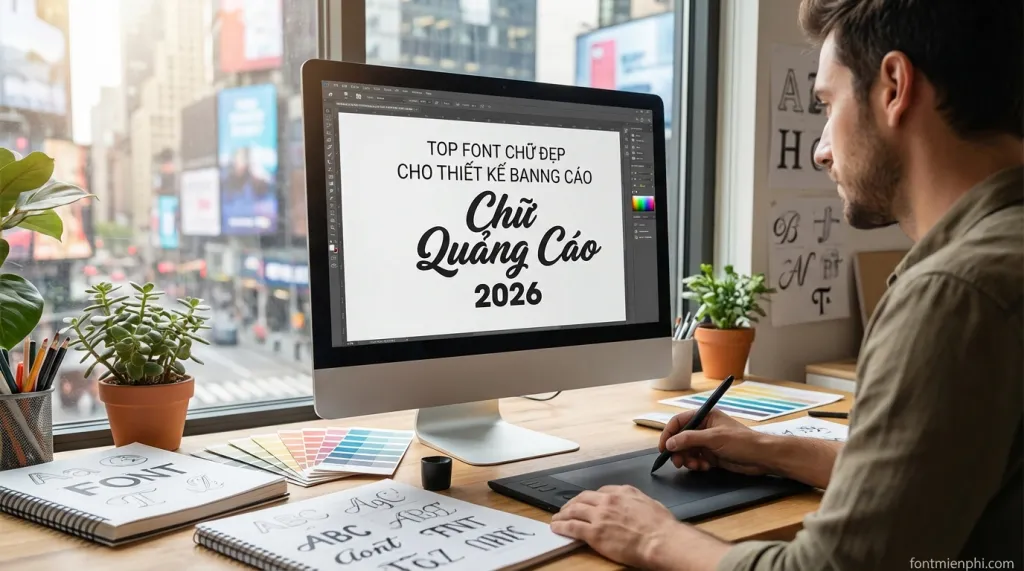
Trong bối cảnh quảng cáo kỹ thuật số ngày càng cạnh tranh, việc lựa chọn font chữ phù hợp cho banner không chỉ là một quyết định thẩm mỹ mà còn là yếu tố chiến lược quyết định hiệu quả truyền thông. Một font chữ đẹp, dễ đọc và phù hợp có thể ngay lập tức thu hút sự chú ý, truyền tải thông điệp rõ ràng và củng cố nhận diện thương hiệu. Bài viết này sẽ đi sâu phân tích tầm quan trọng của font chữ, các nguyên tắc lựa chọn, dự đoán xu hướng cho năm 2026 và giới thiệu những font chữ hàng đầu, giúp bạn tạo ra những banner quảng cáo tối ưu và ấn tượng nhất.
Top Font Chữ Đẹp Cho Thiết Kế Banner Quảng Cáo 2026
I. Tầm Quan Trọng Của Font Chữ Trong Thiết Kế Banner Quảng Cáo
Font chữ không chỉ là phương tiện truyền tải văn bản; chúng là một phần không thể thiếu của ngôn ngữ hình ảnh, mang theo cảm xúc, phong cách và cá tính riêng. Trong lĩnh vực thiết kế banner quảng cáo, nơi mà mỗi mili giây đều quý giá để thu hút sự chú ý của người xem, việc lựa chọn font chữ đóng vai trò then chốt. Một font chữ được chọn lọc kỹ lưỡng có thể biến một thông điệp đơn thuần thành một tuyên bố mạnh mẽ, dễ dàng đi vào tâm trí khách hàng mục tiêu.
Vai trò của font chữ trong banner quảng cáo có thể được nhìn nhận qua nhiều khía cạnh. Đầu tiên, chúng giúp tạo ra ấn tượng đầu tiên. Trong một không gian kỹ thuật số đầy rẫy thông tin, banner quảng cáo chỉ có vài giây để gây ấn tượng. Font chữ độc đáo, phù hợp có thể làm nổi bật banner của bạn giữa hàng trăm quảng cáo khác, kích thích sự tò mò và khuyến khích người xem dừng lại để đọc kỹ hơn. Thứ hai, font chữ truyền tải cảm xúc và giá trị thương hiệu. Một font serif cổ điển có thể gợi lên sự sang trọng và đáng tin cậy, trong khi một font sans-serif hiện đại lại thể hiện sự năng động và thân thiện. Việc lựa chọn font chữ đồng điệu với bản sắc thương hiệu giúp củng cố thông điệp và xây dựng nhận diện thương hiệu nhất quán. Thứ ba, tính dễ đọc của font chữ quyết định khả năng truyền tải thông điệp. Banner quảng cáo thường chứa thông tin ngắn gọn, súc tích. Nếu font chữ quá cầu kỳ, khó đọc hoặc không phù hợp với kích thước hiển thị, thông điệp sẽ bị mất đi, dẫn đến lãng phí nỗ lực và chi phí quảng cáo. Cuối cùng, font chữ góp phần tạo nên sự khác biệt. Trong một thị trường cạnh tranh, việc sử dụng các font chữ độc đáo, chưa phổ biến hoặc được tùy chỉnh có thể giúp thương hiệu của bạn nổi bật, tạo dấu ấn riêng trong tâm trí khách hàng.
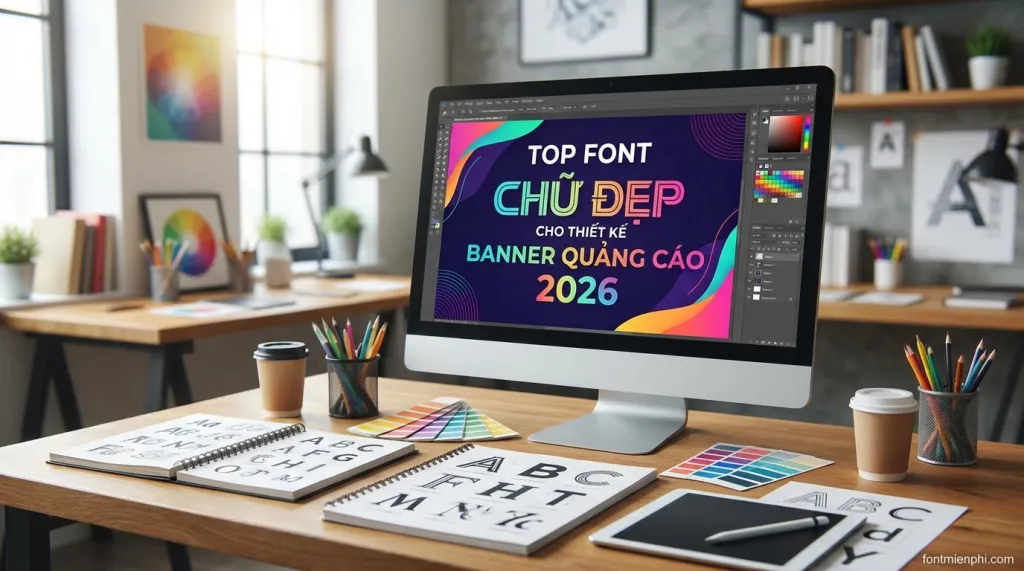
II. Các Nguyên Tắc Vàng Khi Lựa Chọn Font Chữ Cho Banner Quảng Cáo
Để tối ưu hóa hiệu quả của banner quảng cáo, việc lựa chọn font chữ cần tuân thủ một số nguyên tắc cơ bản nhưng vô cùng quan trọng. Những nguyên tắc này không chỉ đảm bảo tính thẩm mỹ mà còn nâng cao khả năng truyền tải thông điệp và tương tác với người xem.
1. Tính Dễ Đọc (Legibility)
Đây là nguyên tắc hàng đầu và không thể bỏ qua. Font chữ dù đẹp đến mấy cũng trở nên vô nghĩa nếu người xem không thể đọc được nội dung. Đối với banner quảng cáo, nơi không gian và thời gian đều hạn chế, tính dễ đọc càng trở nên cấp thiết.
– Chọn font có khoảng cách chữ (kerning) và khoảng cách dòng (leading) hợp lý.
– Tránh các font quá mảnh, quá cầu kỳ hoặc có độ tương phản thấp với màu nền.
– Đảm bảo font chữ hiển thị rõ ràng trên nhiều kích thước màn hình và thiết bị khác nhau, từ điện thoại di động đến màn hình máy tính lớn.
– Ưu tiên các font có các ký tự rõ ràng, không dễ nhầm lẫn (ví dụ: “I” và “l”, “0” và “O”).
2. Phù Hợp Với Thương Hiệu Và Thông Điệp
Font chữ phải là một phần mở rộng của bản sắc thương hiệu và nội dung quảng cáo.
– Nếu thương hiệu của bạn hướng đến sự sang trọng, cao cấp, các font serif cổ điển hoặc hiện đại có thể là lựa chọn lý tưởng.
– Đối với các thương hiệu công nghệ, startup hoặc muốn thể hiện sự hiện đại, năng động, font sans-serif thường được ưu tiên.
– Thông điệp quảng cáo cũng ảnh hưởng đến việc chọn font. Một chương trình khuyến mãi giảm giá có thể dùng font mạnh mẽ, thu hút, trong khi thông điệp về sự bền vững, thân thiện môi trường có thể dùng font mềm mại, hữu cơ hơn.
– Đảm bảo sự đồng bộ với các kênh truyền thông khác của thương hiệu để tạo sự nhận diện nhất quán.
3. Khả Năng Mở Rộng (Scalability)
Banner quảng cáo xuất hiện ở nhiều vị trí và kích thước khác nhau. Một font chữ tốt phải giữ được tính dễ đọc và thẩm mỹ khi được phóng to hay thu nhỏ.
– Font chữ cần duy trì độ sắc nét, không bị vỡ nét hay mờ khi thay đổi kích thước.
– Kiểm tra font trên các mock-up banner ở nhiều kích thước khác nhau trước khi đưa vào sử dụng chính thức.
– Các font được thiết kế tối ưu cho web (web-safe fonts) thường có khả năng mở rộng tốt hơn.
4. Cảm Xúc Và Tâm Lý Học Font Chữ
Mỗi loại font chữ mang một “tính cách” và gợi lên những cảm xúc khác nhau.
– **Serif:** Gợi cảm giác truyền thống, đáng tin cậy, sang trọng, uy tín (thường dùng cho các ngành tài chính, luật, giáo dục, thời trang cao cấp).
– **Sans-serif:** Hiện đại, tối giản, thân thiện, dễ tiếp cận, rõ ràng (phổ biến cho công nghệ, thương mại điện tử, dịch vụ).
– **Script/Handwritten:** Nghệ thuật, cá tính, độc đáo, thân mật (thường dùng cho các sản phẩm thủ công, sự kiện đặc biệt, thương hiệu cá nhân).
– **Display:** Mạnh mẽ, thu hút, độc đáo, thường dùng cho tiêu đề lớn, tạo điểm nhấn mạnh (giải trí, game, sản phẩm mới).
Hiểu rõ tâm lý học font chữ giúp bạn lựa chọn font phù hợp nhất với mục tiêu truyền thông.
5. Hỗ Trợ Đa Ngôn Ngữ Và Ký Tự Đặc Biệt
Đối với thị trường Việt Nam, việc font chữ hỗ trợ đầy đủ các ký tự tiếng Việt (dấu, chữ cái đặc biệt như “ă”, “â”, “đ”, “ê”, “ô”, “ơ”, “ư”) là yếu tố cực kỳ quan trọng.
– Một font không hỗ trợ tiếng Việt sẽ dẫn đến hiện tượng lỗi font, các ký tự bị biến dạng hoặc hiển thị không đồng nhất, gây ảnh hưởng nghiêm trọng đến tính chuyên nghiệp và dễ đọc của banner.
– **Alex Brush**
– Đặc điểm: Alex Brush là một font script mang phong cách viết tay với nét cọ mềm mại, uyển chuyển và sang trọng. Nó có một vẻ ngoài tinh tế và lãng mạn, tạo cảm giác thanh lịch.
– Lý do phù hợp cho banner: Rất phù hợp cho các ngành như cưới hỏi, mỹ phẩm, trang sức hoặc các dịch vụ cao cấp cần sự mềm mại, tinh tế. Tuy nhiên, cần sử dụng ở